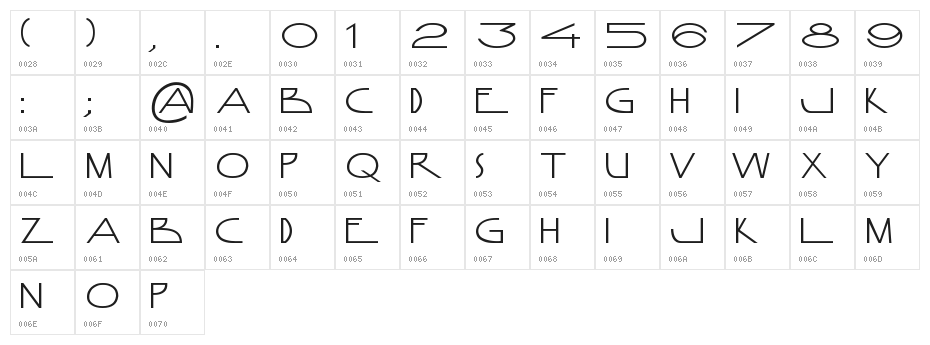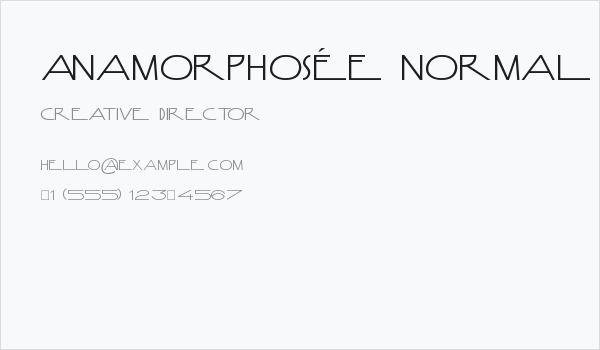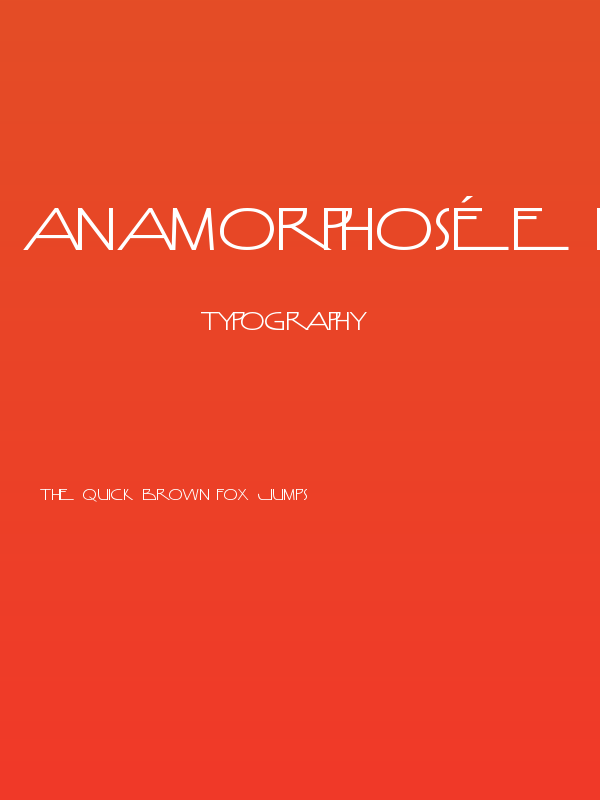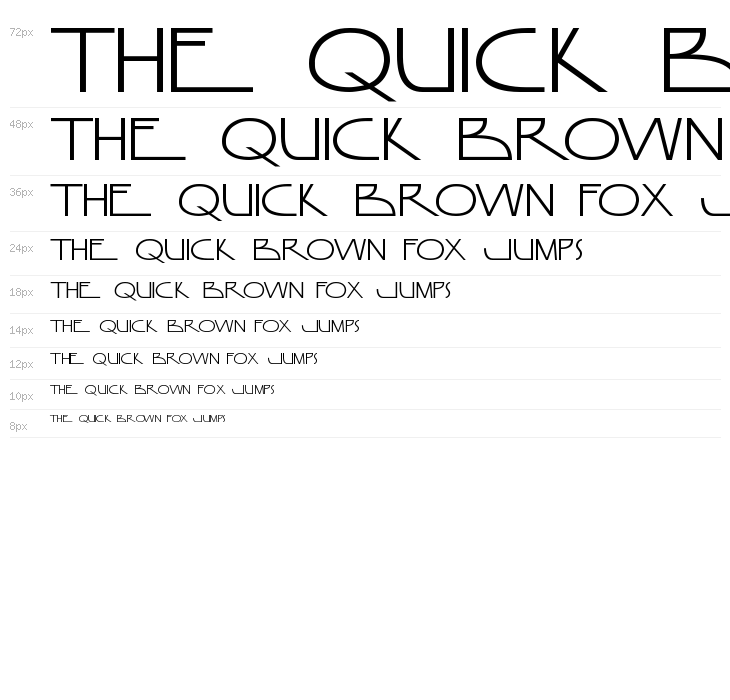
Anamorphosée Normal Font
| Progetti proposti | Ideal for technology branding, sci-fi movie posters, modern art installations, and innovative product packaging. |